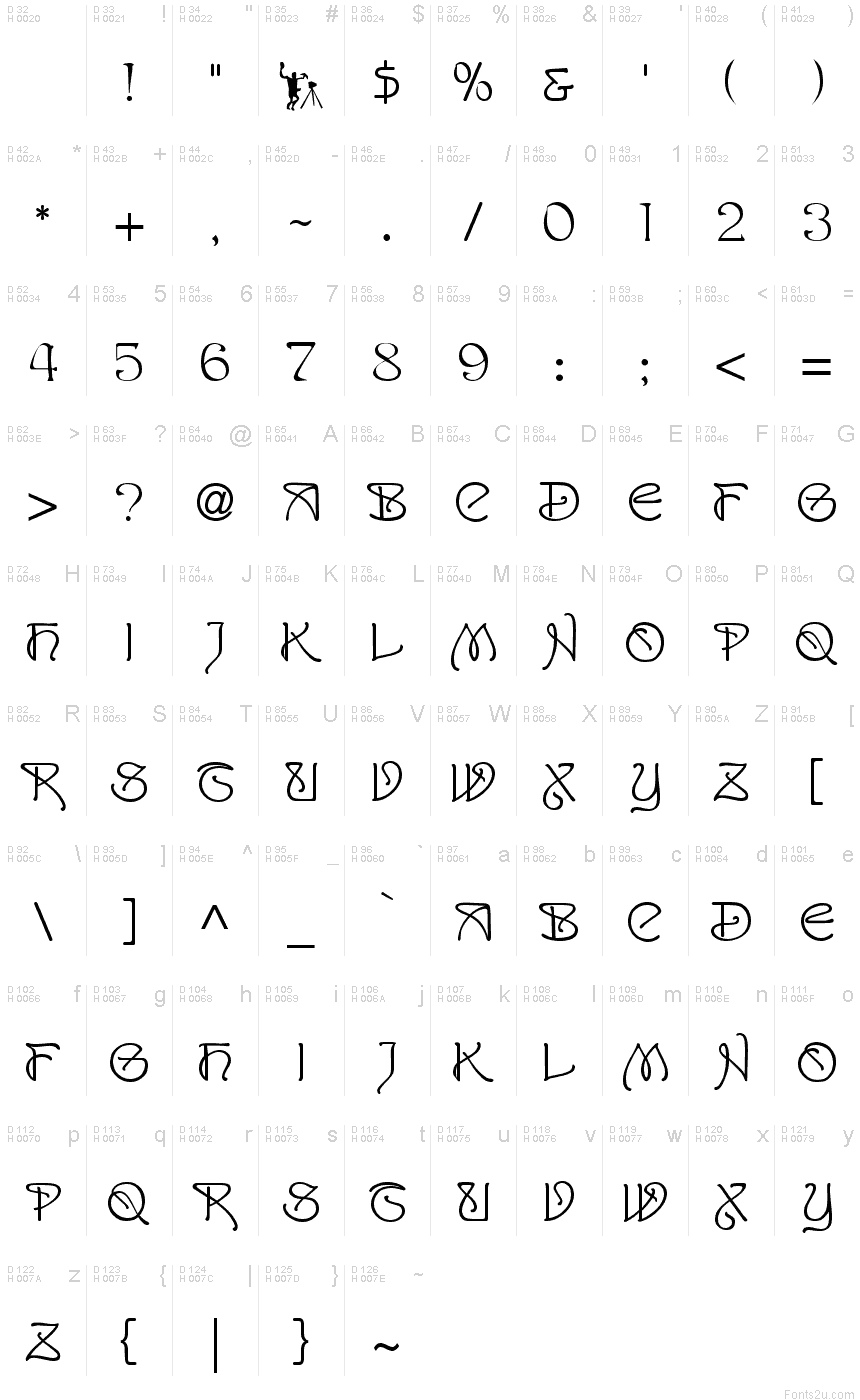
San Remo
San Remo od Typographer Mediengestaltung to darmowy krój displayowy w stylu Art Nouveau, wyróżniający się długimi, zapętlonymi liniami oraz lekkim, smukłym rytmem. Litery sprawiają wrażenie rysowanych jednym, ciągłym ruchem, łącząc wąskie, pionowe formy z szerokimi łukami, co nadaje całości ornamentalny, zwiewny i nieco teatralny charakter.
Świetnie sprawdzi się na plakatach, w brandingu butików, na opakowaniach muzycznych, okładkach książek oraz w menu kawiarni, gdzie ozdobny nagłówek nadaje ton. Jako darmowy font, San Remo najlepiej wypada w krótkich tekstach, takich jak tytuły, nagłówki czy monogramy, ponieważ jego wydłużone pętle i miękkie zawijasy potrzebują przestrzeni, aby w pełni ukazać swój charakter.